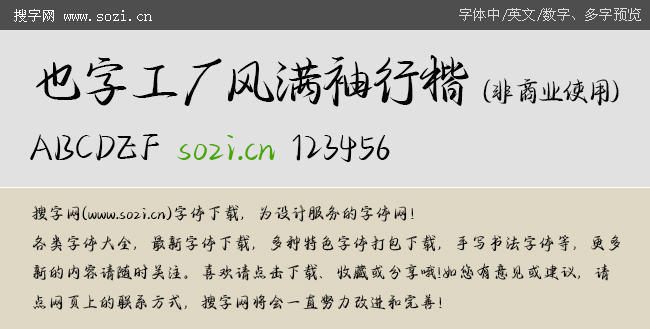
也字工廠風滿袖行楷
搜字網給大家提供一款也字工廠風滿袖行楷(非商業使用)中文字體下載,也字工廠風滿袖行楷是一款手寫書法字體,字體書寫流暢自然,字形瀟灑大方。具有很好的視覺效果。適合應用于藝術設計、平面宣傳設計、網頁設計、海報設計等應用(此字體為個人非商用版,商用可以聯系:官方網址:https://yefont.com/home,聯系方式:13798980448)。